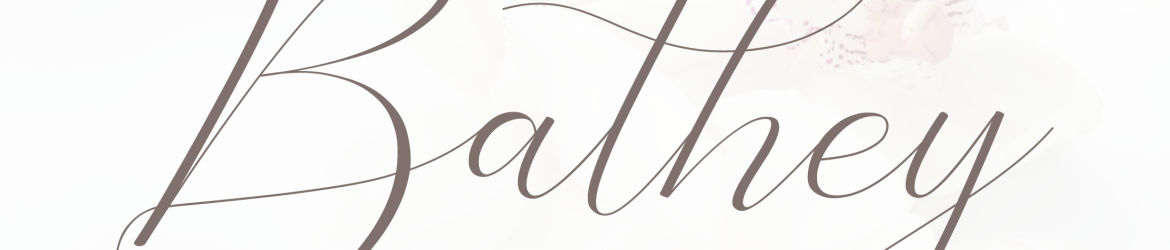
Bathey Calligraphy Font
Batey Calligraphy Font é uma seleção inovadora de tipografia que combina influências modernas com o estilo tradicional da escrita à mão. Perfeita para designers, Batey oferece personalidade forte e se destaca como uma fonte de assinatura perfeita para criações visuais variadas. Esta fonte foi projetada pela 0001themes sob a supervisão do designer Samantha Signature, conhecida por suas habilidades inovadoras na área da tipografia. Batey é ideal para desenvolver um design exclusivo que atende desde logotipos e selos até cabeçalhos de posters, capas de livros, cartões de visita, designs fashion, anúncios e embalagens de produtos. Batey também brilha em invitações ao casamento e citações escritas à mão. Suas linhas fluidas e suas cores vibrantes são perfeitas para tornar qualquer projeto ainda mais único e emocionante. Esta fonte é uma escolha inteligente para designers que buscam expressar a personalidade de seus projetos através de um design tipográfico impecável.